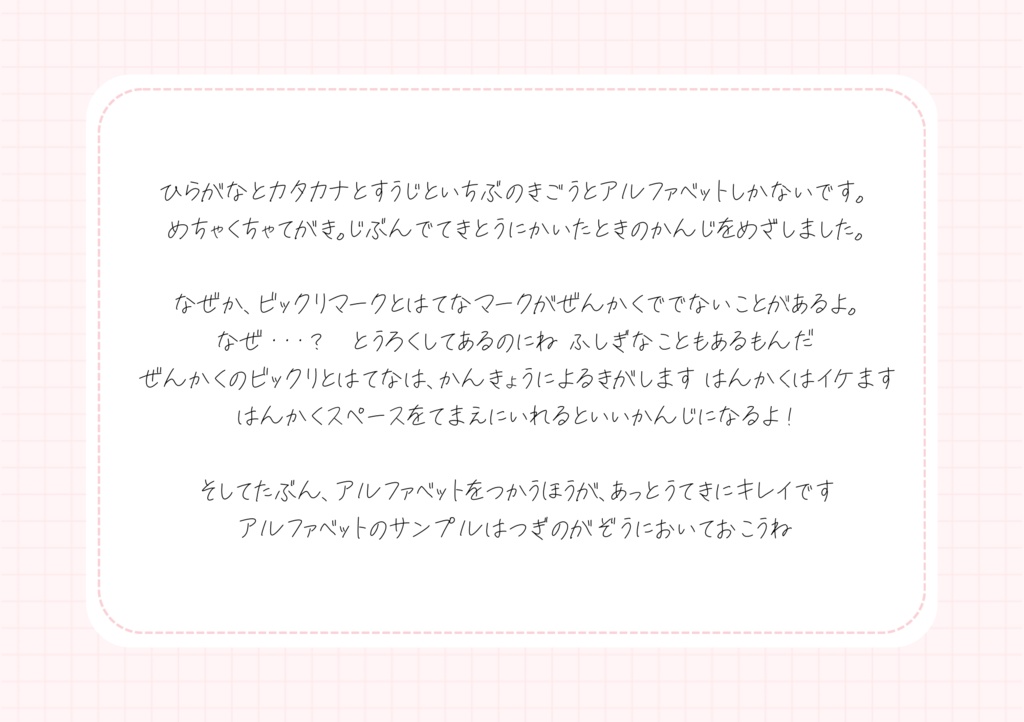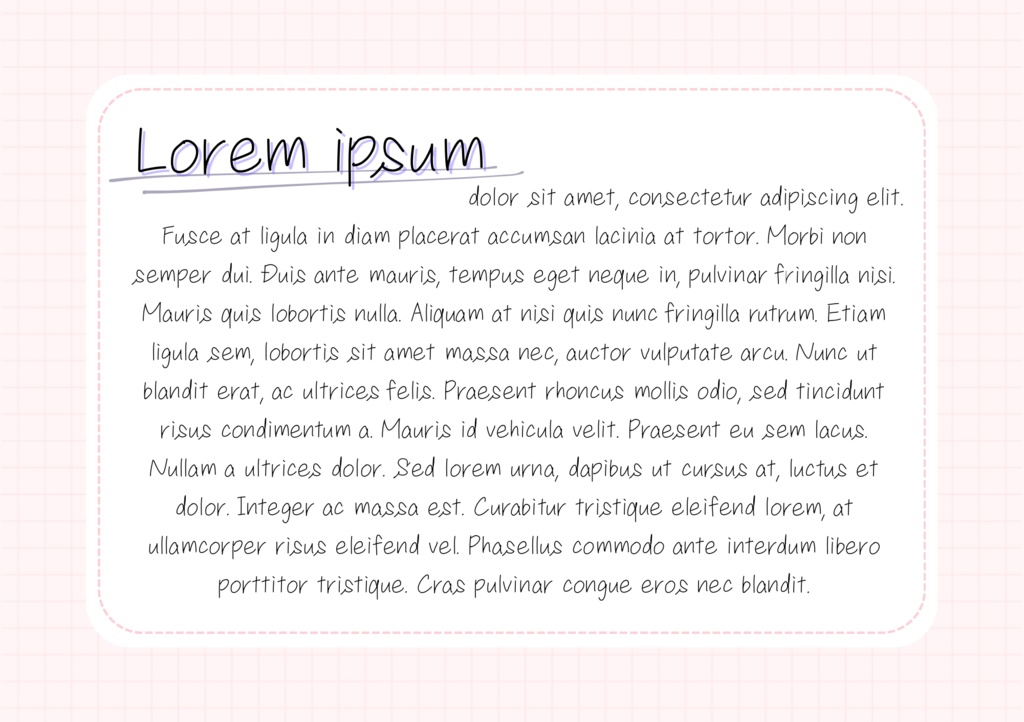
さけおフォント
夜な夜なちまちま手書きした字を詰めたものです。 ひらがな・カタカナ・アルファベット・数字・一部記号が含まれています。 あらゆることに文句を言ってはいけません。ゆるく自由に使うフォントです。 【ファイル種別】 TTFファイル 【使用可能範囲】 ・商用、非商用問わず使用可能です。広告等の各種Web媒体、ロゴ、動画、同人誌を含む二次創作物への利用もOKです。成人向けも問題ありません。 ・公序良俗に反するものには利用不可です。 【利用規約・注意事項】 ・著作権を放棄していません。自作発言はご遠慮ください。 ・当フォントのダウンロード・利用により発生したトラブル、不具合、損害の類について一切の責任を負いません。また、サポート等はしておりません。お問い合わせはご遠慮ください。 ・予告なく内容・利用規約を変更する場合がございます。 ・一部のOS、ソフトウェアでは使用できない場合がございます。 ・使用報告は不要ですが、あるととってもうれしいです! 【禁止事項】 ・データの改変 ・無断転載、再配布 ・販売 ・商標登録